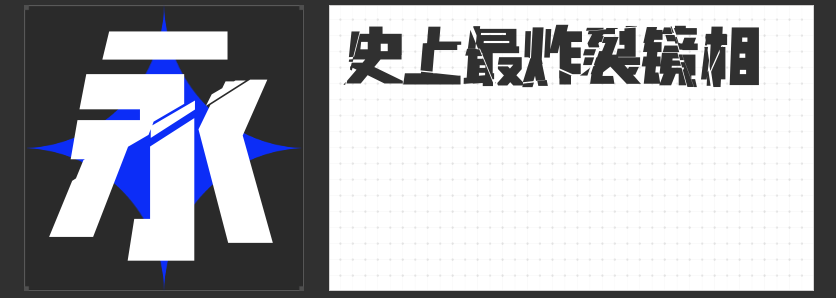
四款个性十足的字库字体推荐
在设计领域,字体不仅是信息的载体,更是作品风格的体现。选择一款合适的字体,能为设计作品增添独特的个性色彩。今天,为大家推荐四款来自励字字库的个性字体,它们各自拥有鲜明的风格特点,能够为设计作品带来不一样的视觉冲击。
这款现代创意型黑体,以其厚重的字型略带开放性,打破了传统黑体的刻板印象。笔画粗细不均,横竖笔画呈梯形分布,撇、捺、点等笔画更是巧妙融入梯形元素,整体风格偏硬而富有现代文艺气息。在设计中使用,能够瞬间提升作品的现代感和创意性,让信息传达更加生动有力。
如果说有一款字体能像铁拳一样直击人心,那一定是励字铁拳简 超级黑。笔画粗壮、字面宽大,饱满的块面感与折角圆设计相结合,带来强烈的视觉冲击。它犹如一拳重击,直击观众的心灵,让设计作品在众多信息中脱颖而出。无论是海报、广告还是品牌标识,都能轻松驾驭。
三、励字多重人格简
这款字体借鉴了影视中人格分裂的表现手法,将碎裂镜子的效果运用在字体上,营造出错乱感、炸裂感和冲击力。排版时,独特的纹理感让作品更加引人注目。它适合用于表达复杂情感或多元主题的设计作品,如艺术展览海报、音乐会宣传等。
逆反差圆弧字体,在直线版的基础上融入了弧线处理,笔画粗细对比明显,弧度饱满。中宫较大,重心平稳,笔画对称,整体风格既硬朗又柔和。这款字体在设计中能够平衡各种风格,既适合正式场合的稳重表达,也能在创意设计中展现独特的韵味。
以上四款励字字库字体,每一款都拥有独特的个性和魅力。它们不仅丰富了设计作品的视觉层次,更让信息传达更加生动有力。选择一款合适的字体,让你的设计作品在众多作品中脱颖而出,展现独特的个性色彩。